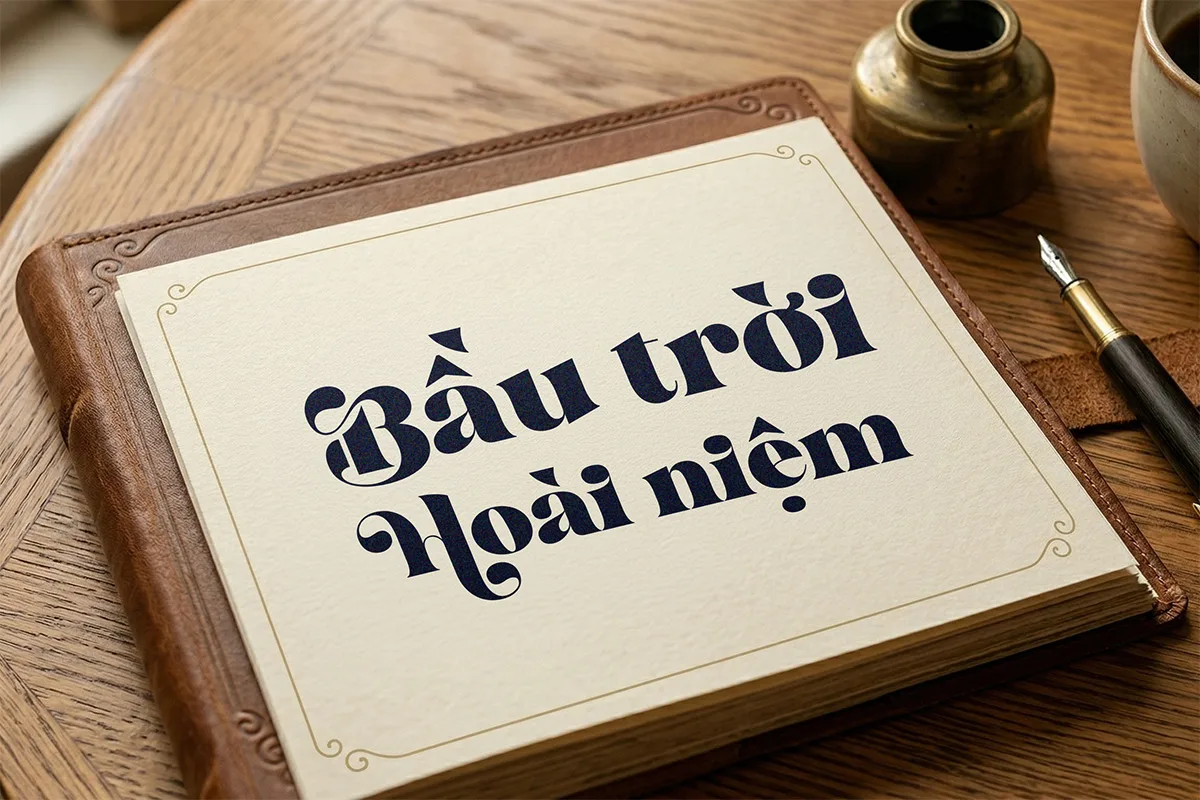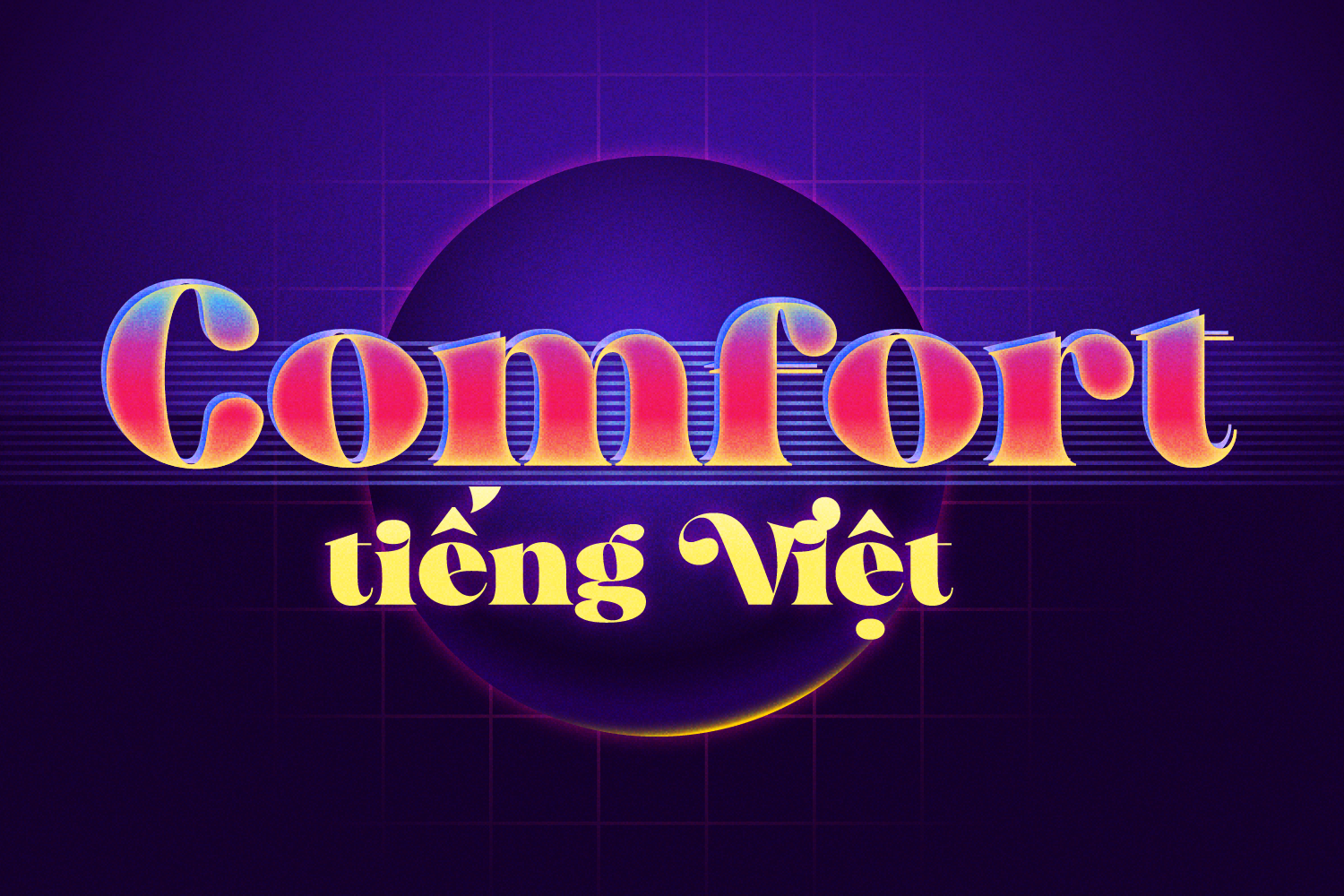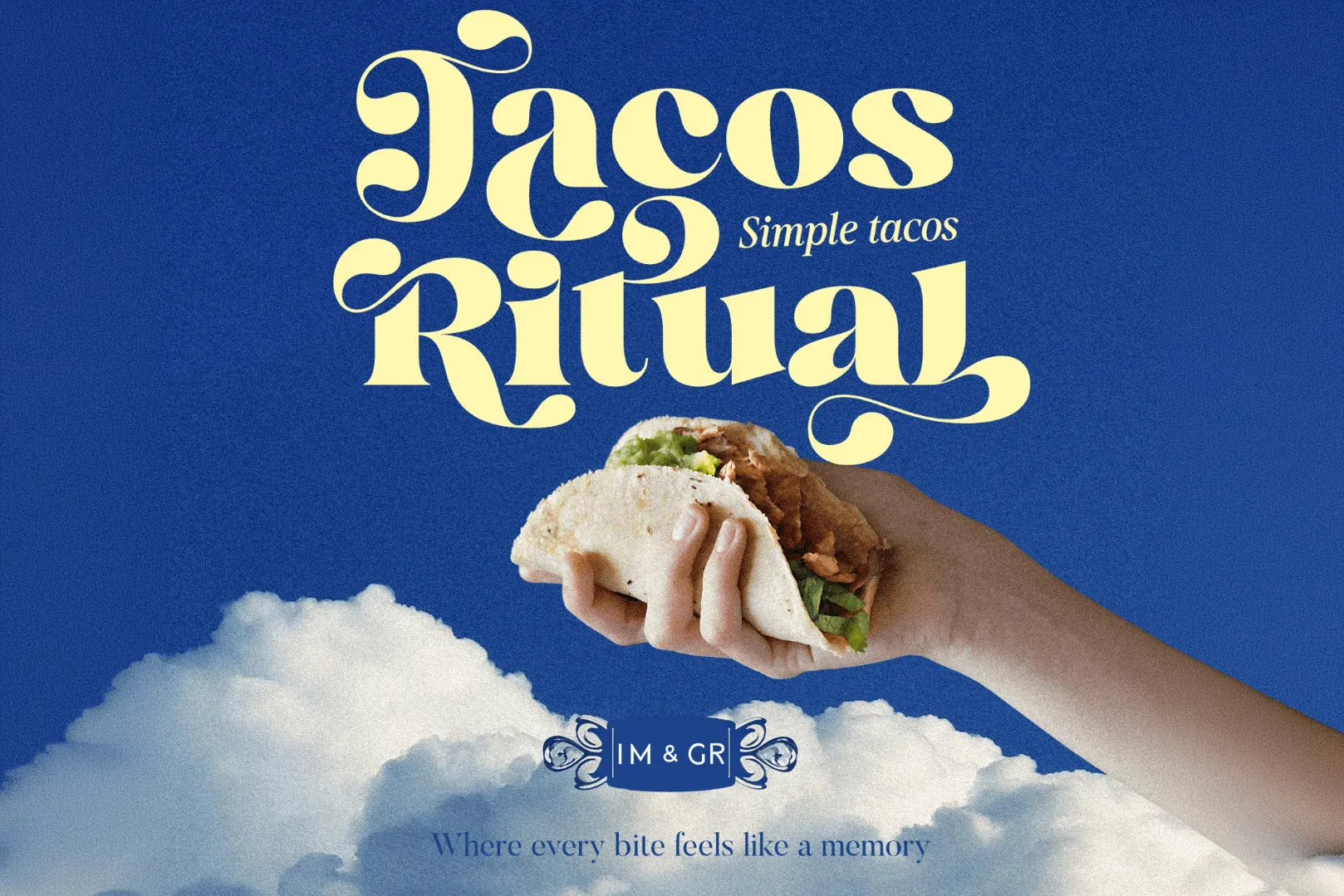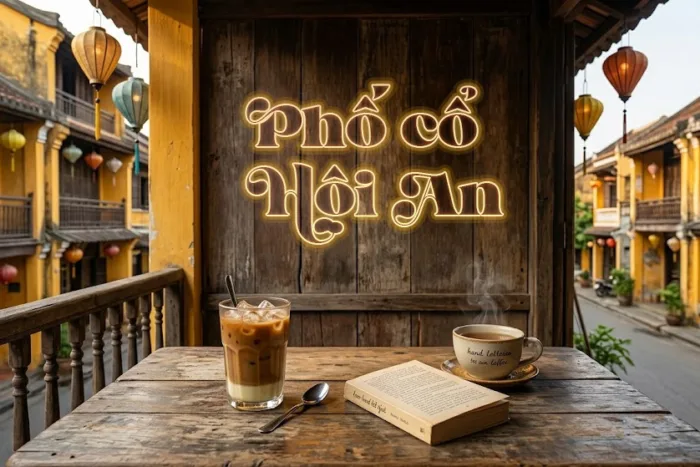
DVN Comfort: Phông chữ Display Serif phong cách Retro 70s
DVN Comfort là một phông chữ hiển thị (Display Serif) mang đặc trưng của phong cách retro thập niên 1970 với cấu trúc nét đậm và độ tương phản dày mỏng rõ ràng. Đặc điểm kỹ thuật nổi bật của font là các góc nhọn cùng phần chân chữ (serif) đều được bo tròn, kết hợp với các nét cuộn xoáy (swash) kéo dài ở chữ in hoa và đuôi chữ thường. Cấu trúc này giúp phá vỡ các đường nét cứng nhắc, tạo ra một tổng thể chữ đầy đặn, có tính liên kết cao và mang lại hiệu ứng thị giác thân thiện, mềm mại.
Về mặt ứng dụng, phông chữ này được thiết kế chuyên biệt cho các đoạn văn bản ngắn cần sự thu hút cao như tiêu đề lớn, thiết kế logo và hệ thống nhận diện thương hiệu. Nhờ phom chữ mang lại cảm giác ngon miệng và ấm cúng, DVN Comfort phát huy tối đa công năng trong các dự án thuộc ngành F&B (bao bì thực phẩm, menu, biển hiệu nhà hàng, tiệm bánh). Đồng thời, đây cũng là lựa chọn tối ưu cho thiết kế nhãn mác, poster của các thương hiệu mang định hướng vintage, sản phẩm thủ công hoặc phong cách sống.